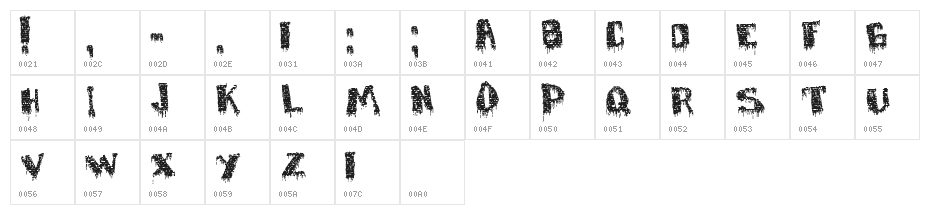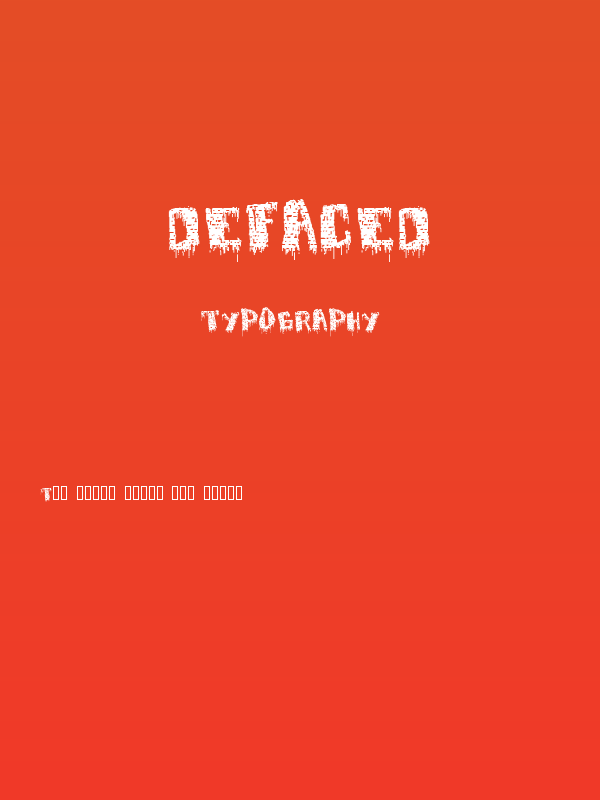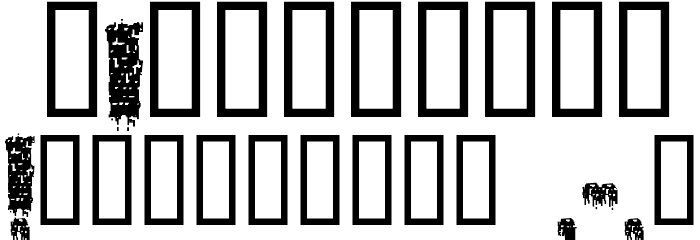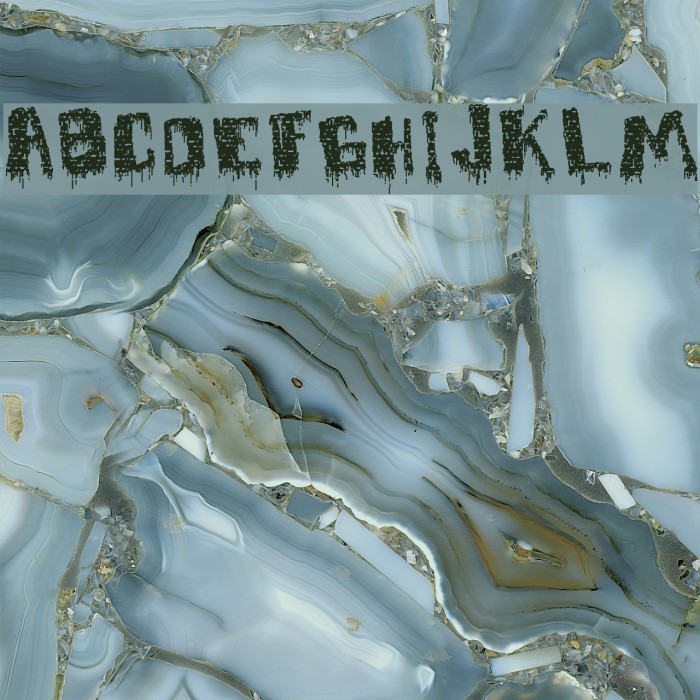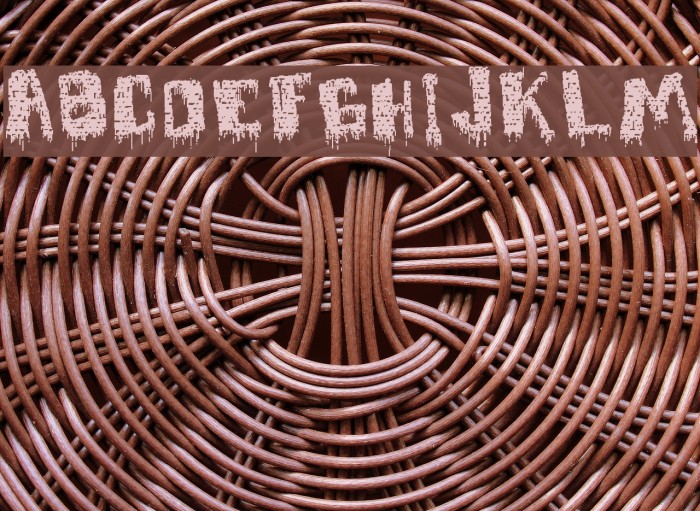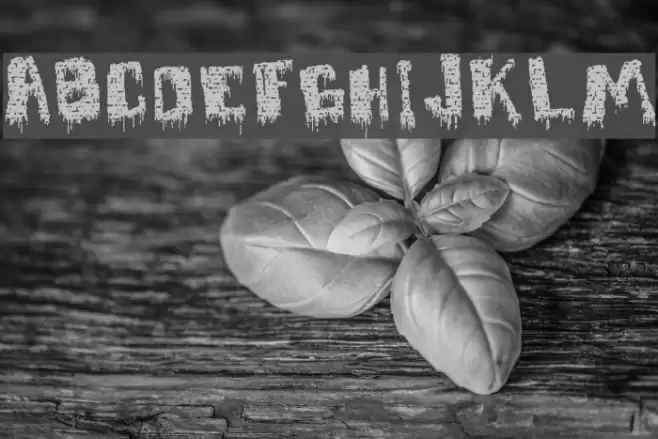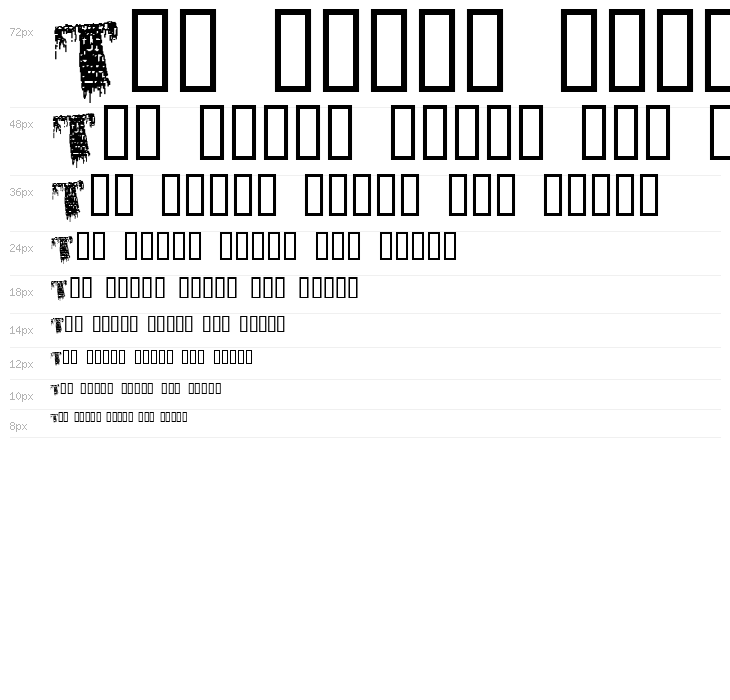
deFaced Font
| Gesamtstil | Grunge, Edgy, Artistic |
| Anwendungsfall | Headlines, Posters, Branding |
| Vorgeschlagene Projekte | Ideal for album covers, event posters, streetwear branding, and horror-themed designs. |